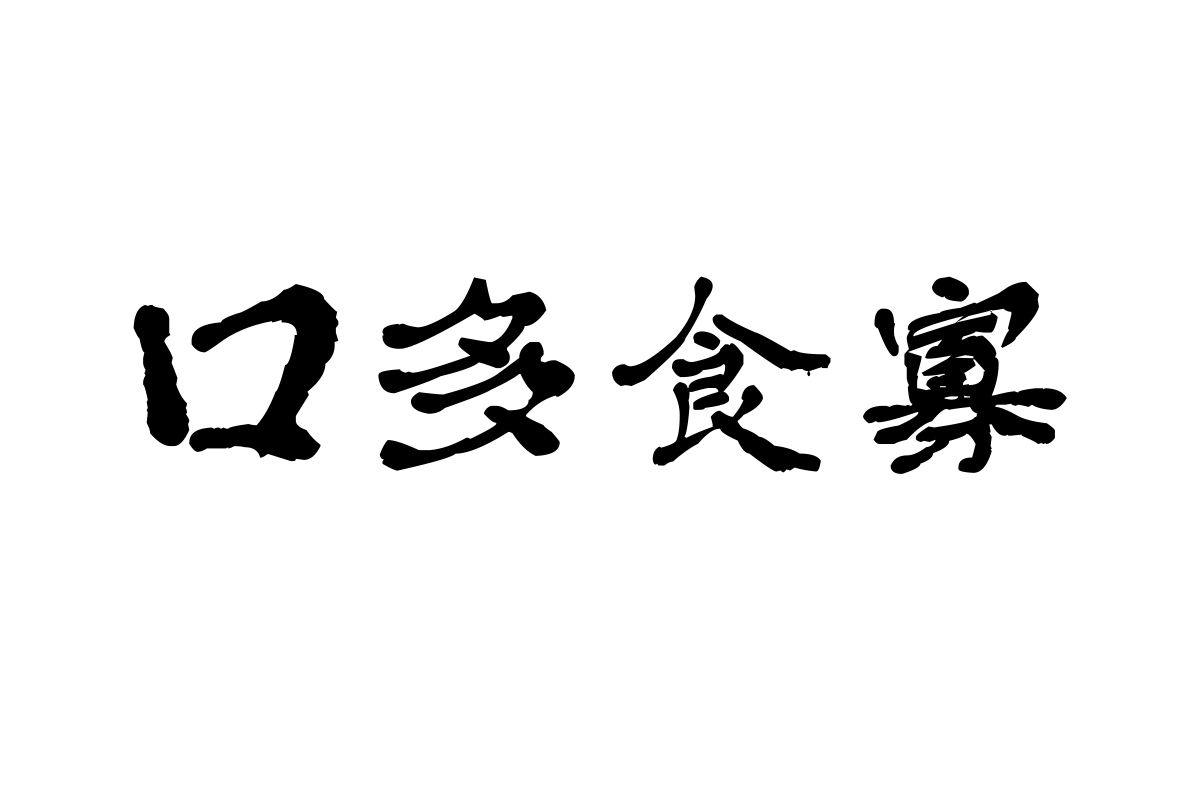
汉标熟宣毛笔体是一款具有独特风格的字体,它结合了现代设计元素和传统书法艺术。这种字体的特点是笔画流畅自然,结构紧凑有力,给人一种古朴典雅的感觉。它适用于各种需要书写的场合,如广告、海报、书籍等。
汉标熟宣毛笔体的字形特点包括:
– 笔画粗细适中,既有力度又有柔美,适合书写各种字体。
– 结构紧凑,笔画连接紧密,给人一种整齐有序的感觉。
– 字形饱满,线条流畅,给人一种优美和谐的视觉享受。
总的来说,汉标熟宣毛笔体是一款非常适合现代设计的字体,它能够很好地融入各种场景,为文字增添一份古典韵味。